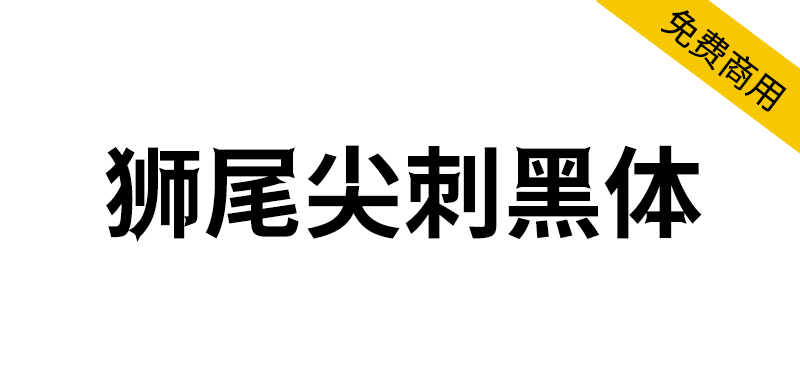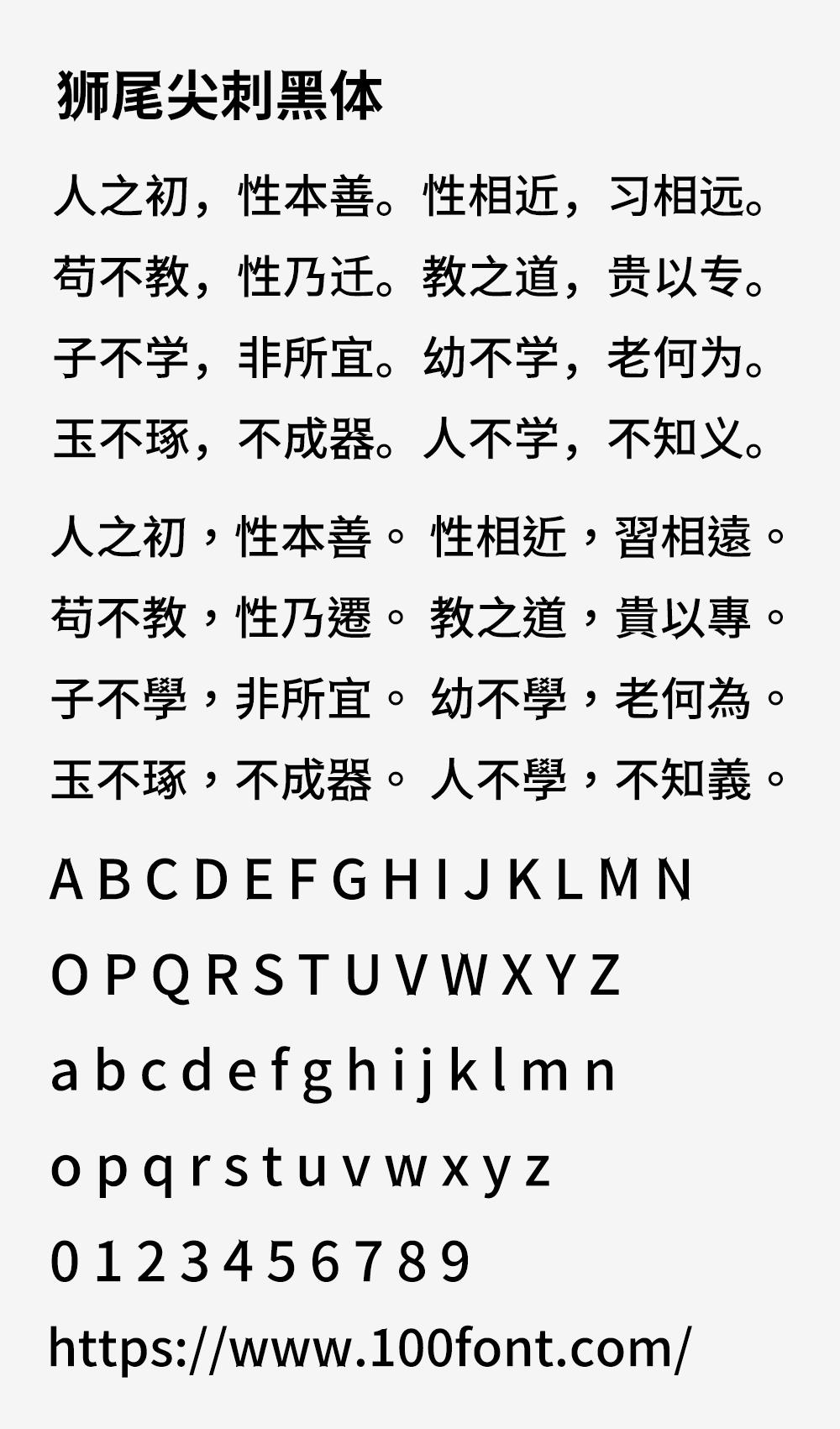
狮尾尖刺黑体基于思源黑体的转角长尖刺和拔脚改造,更加简明现代化的字体。狮尾尖刺黑体的特色是「口」字的4个转角长尖刺。和思源黑体一样,有7种字重,支持简体中文、繁体中文、韩文与日文,可以免费商用,欢迎大家自由应用、自由优化、自由改作!
狮尾尖刺黑体与「狮尾尖腿黑体」差别在有没有拔脚,「拔脚」就是会有较少的笔画,例如移除「口」字的左右下角会多出的短线条。有拔脚的字会较圆,但是会造成有些字因直接去掉腿后左右不平衡、左右不对衬的「悬空」问题。改使用「腿」系列字体就不会有这个问题。